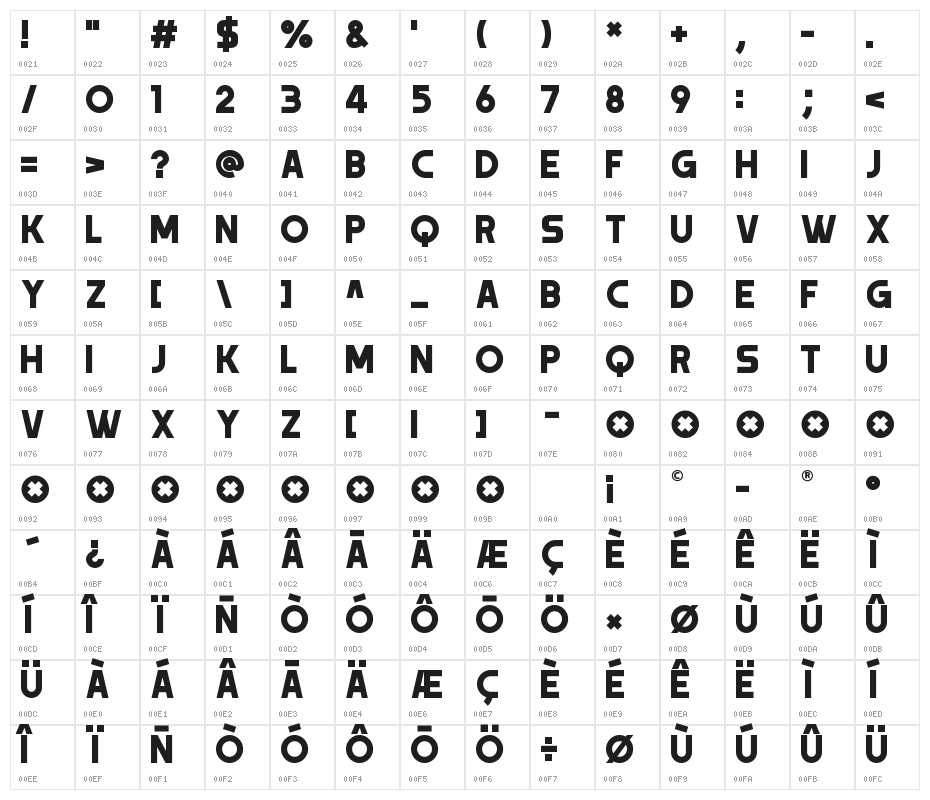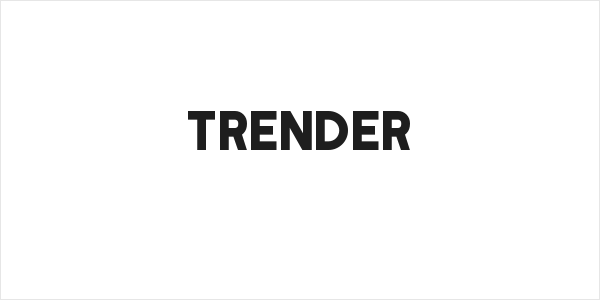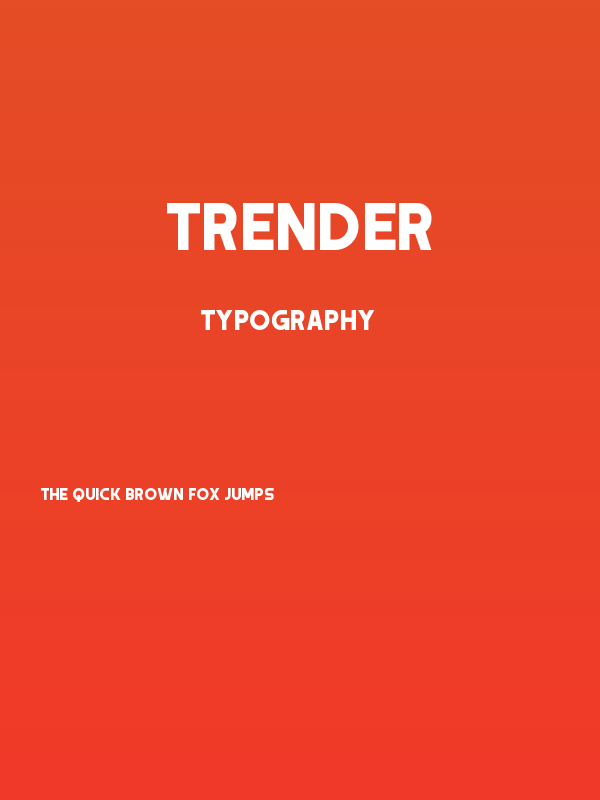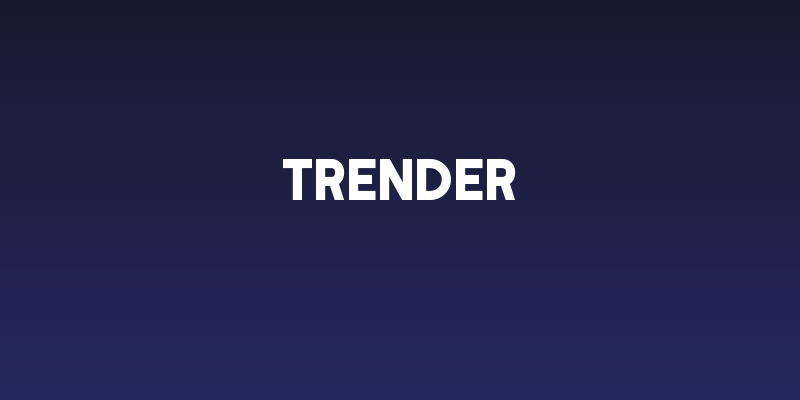
Trender Font
| Kategorien | Thick |
| Vorgeschlagene Projekte | Ideal for branding, headlines, posters, and any project requiring a strong, modern typeface. |